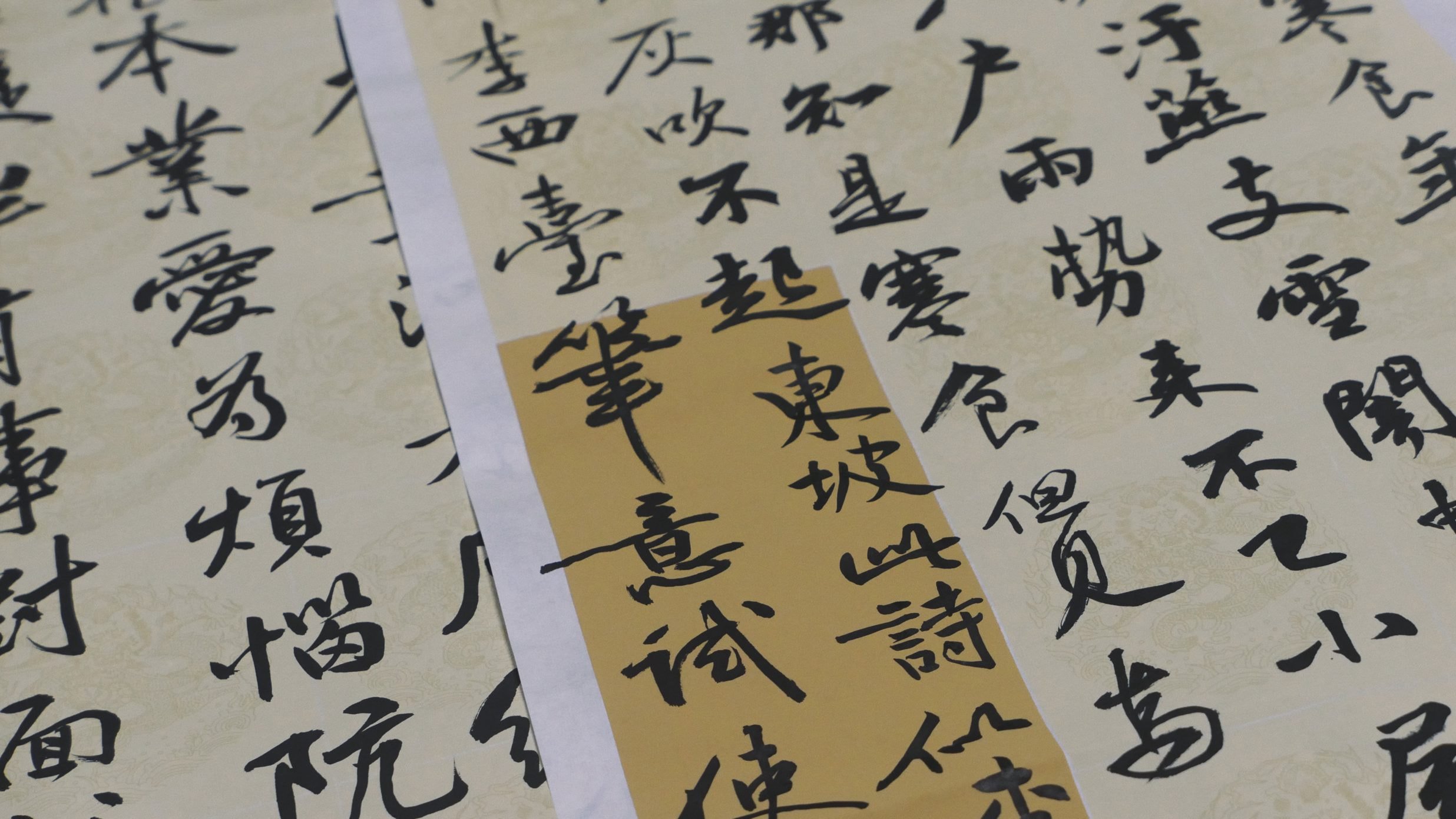
中国书法是汉字的书写艺术,从甲骨文、石鼓文、金文(钟鼎文)演变而为大篆、小篆、隶书,至定型于东汉、魏、晋的草书、楷书、行书等,书法一直散发着艺术的魅力。
书法中所提到的字体是千百年来人们选择的结果,更是一个时代的凝结,从印刷时代起,字体均由人工设计,我们所熟悉的隶书、楷体、草书、宋体等等分别是某类相似风格的许多字体的集合,而不是一种字体。
传统字体可以分为五大类:篆书、隶书、草书、楷书、行书,每一大类传统字体又有细分的小类,如篆书又分大篆、小篆,楷书又有魏碑、唐楷之分,草书有章草、今草、狂草之分。
01 篆书
篆书是大篆、小篆的统称。
篆书的笔法瘦劲挺拔,曲线较多,直线较少。大篆指金文、籀文、六国文字,它们保存着古代象形文字的明显特点;小篆也称“秦篆”,是秦国的通用文字,是大篆简化后的字体,其形体均匀齐整,更容易书写。
大篆《石鼓文》、李斯作品
02 隶书
隶书也叫“隶字”、“古书”,是在篆书基础上,为适应书写便捷的需要产生的字体。
隶书是汉字中常见的一种庄重的字体,它起源于秦朝,在东汉时期达到顶峰,在书法界有“汉隶唐楷”之称。隶书结体扁平、工整、精巧,书写效果略微宽扁,横画长而直画短,讲究“蚕头燕尾”、“一波三折”。
03 草书
广义的草书是指草写的书体;狭义上来讲草书分为章草、今草、狂草。
章草始于篆书向隶书演化的过程,特点是字形扁方,趋横势,结构简约;今草由章草衍进而成,已经完全去掉隶书的“雁尾”笔法,结构趋于长方、纵势。
章草《急就章》、今草《书谱》
狂草比今草更加飘逸奔放,用笔流畅跌宕、笔势骤聚,笔断意连、一气呵成,其运动感与节奏感极强,有震撼人心的力量。
狂草《古诗四帖》
04 楷书
楷书也叫正楷、真书、正书、小楷,由隶书逐渐演变而来,更趋简化,横平竖直。《辞海》书中解释说它“形体方正,笔画平直,可作楷模”。这种汉字字体端正,就是现代通行的汉字手写正体字。
遵循其规律,将中国楷书的发展史分为四个时期:即楷书的萌芽期——秦汉,楷书发展期——魏、晋、南北朝,楷书繁荣期——隋、唐、五代,楷书守成期——宋、元、明、清。
楷书《九成宫醴泉铭》
05 行书
行书,是一种书法统称,分为行楷和行草两种。
它是在楷书的基础上发展而来的、介于楷书、草书之间的一种字体,为了弥补楷书的书写速度太慢和草书的难于辨认而产生的。楷法多于草法的叫“行楷”,草法多于楷法的叫“行草”,行书的实用性和艺术性都比较高,
行楷《兰亭序》、行草《祭侄文稿》
上述提到的五种传统字体是中华文化的凝练与彰显,但是其视觉艺术的学术属性远大于功能属性,在日常生活中,字库字体则更适用于大众识读和普及化发展。